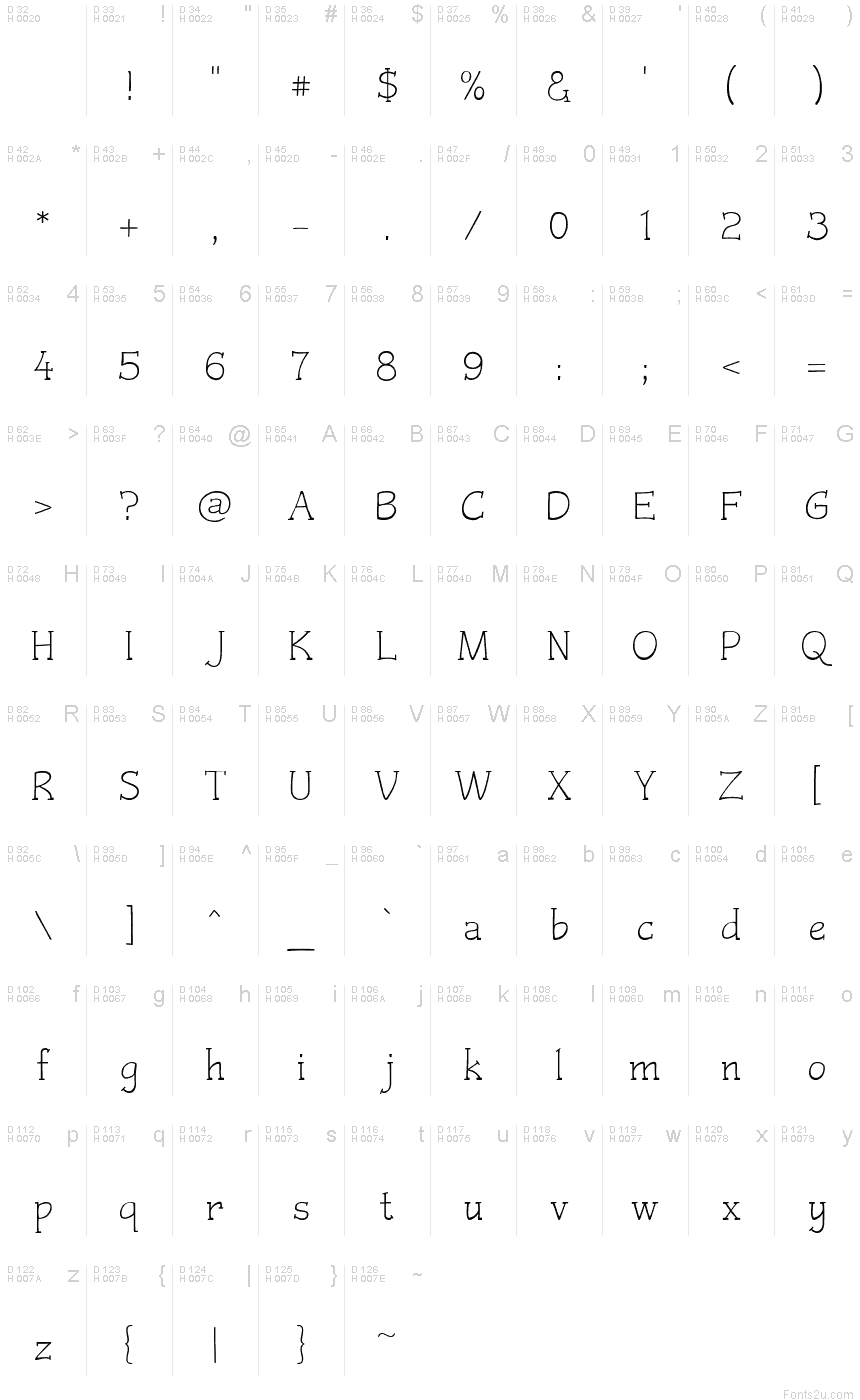
Czaristite
Krój pisma Czaristite autorstwa Grahama Meade’a ma w sobie spokojny, literacki urok, dzięki delikatnie zakrzywionym szeryfom i lekko nieregularnym liniom, które przypominają tusz wsiąkający w miękki papier. To darmowy, szeryfowy font w stylu oldstyle, który łączy elegancję z przystępnością, nadając słowom ludzki, książkowy charakter zamiast chłodnego, mechanicznego wykończenia.
Wybierając Czaristite, zyskujesz szeryfowy krój, który świetnie sprawdza się w składzie redakcyjnym, tomikach poezji, projektach o tematyce historycznej, brandingu vintage, cytatach, wnętrzach książek i wyrafinowanych opakowaniach. Wąskie proporcje pozwalają zmieścić więcej tekstu bez wrażenia ścisku, a subtelna tekstura dodaje ciepła zarówno na ekranie, jak i w druku. Ten darmowy font doskonale wygląda w zestawieniu z czystym krojem bezszeryfowym w nagłówkach i dobrze prezentuje się w średnich rozmiarach, gdzie jego charakter jest najlepiej widoczny.